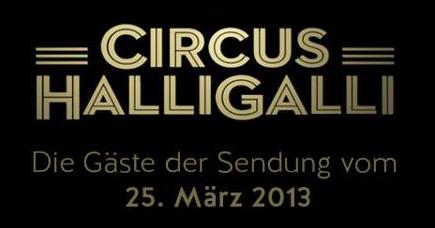
Circus Halli Galli - Überschrift und Untertexte
für unseren Abi-Abschluss ist das Thema Circus Halli Galli. Wir wollen gern versuchen, die Abizeitung dem Layout der Serie nachzuempfinden und sind auf der Suche nach einer Schrift die dem Orginal sehr nahe kommt.
Die Brandon Grotesk von Hannes v. Döhren.? Gibt es von der eine Inline?
Möglicherweise ist die Überschrift eine Gotham. Der Text sollte aber eine Brandon Grotesk sein ...
das Logo müsste Neutraface Display Inline sein.
hier eine alternative:
die schrift darunter könnte brandon grotesque sein: